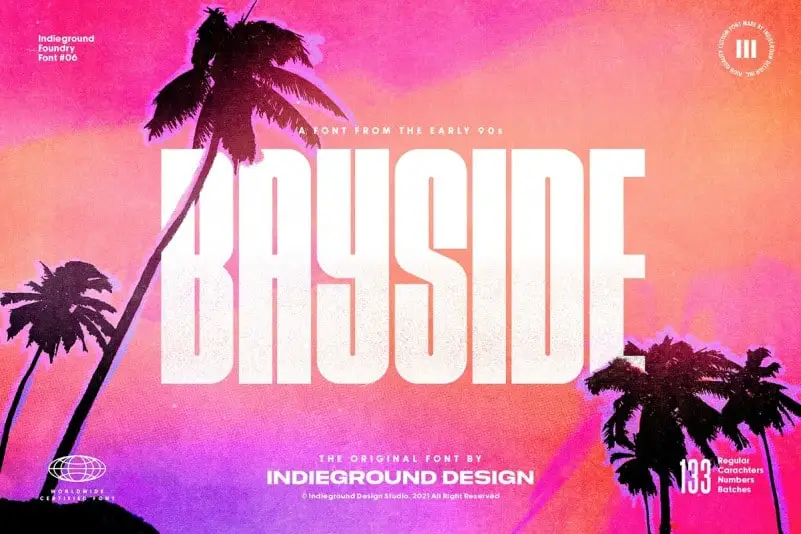
Bayside Display Font Family
A Bayside Display Font é uma família de tipos de exibição contemporânea criada pelo Indieground team com um forte caráter. Inspirada nos atmosferas retro da década de 1980 e 1990 do verão, essa fonte se destaca como perfeita para ambientes elegantes reminiscentes dos Deco Art de Miami da década de 1980. Ela também encaixa-se bem na era das cores neon da década de 1990, tornando-a ideal para artigos modernos que visam otimizar o espaço e dar destaque a títulos pesados. Com seu design atualizado e forte personalidade, essa fonte fornece um impacto imediato em seus trabalhos gráficos. Seu peso regular comercial inclui três diferentes tipos de contração com todos os caracteres do conjunto de uso mostrado na pré-visualização. A Bayside Display Font é perfeita para destacar os textos dos teus trabalhos e dar-lhes um toque assertivo, tornando-a uma excelente escolha para qualquer aplicação em que você precisa de destaque notável no design de títulos pesados.